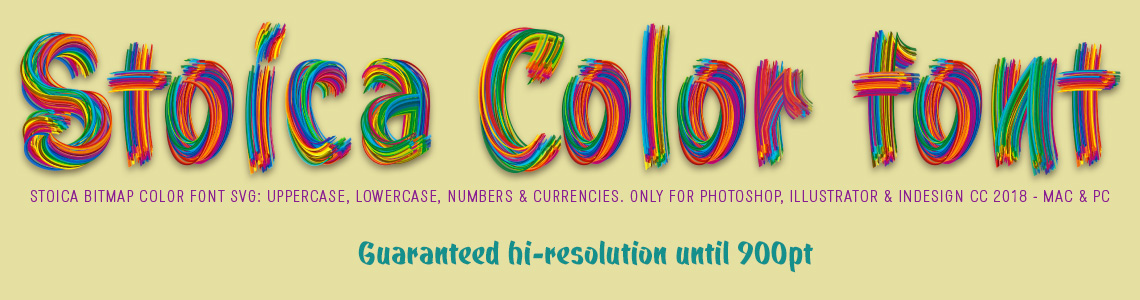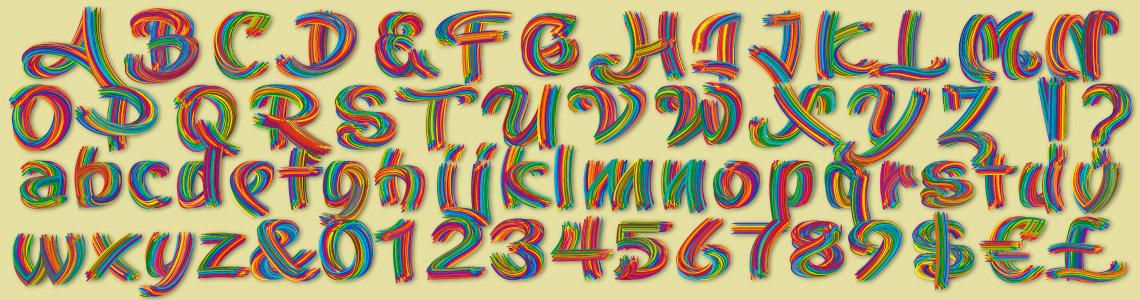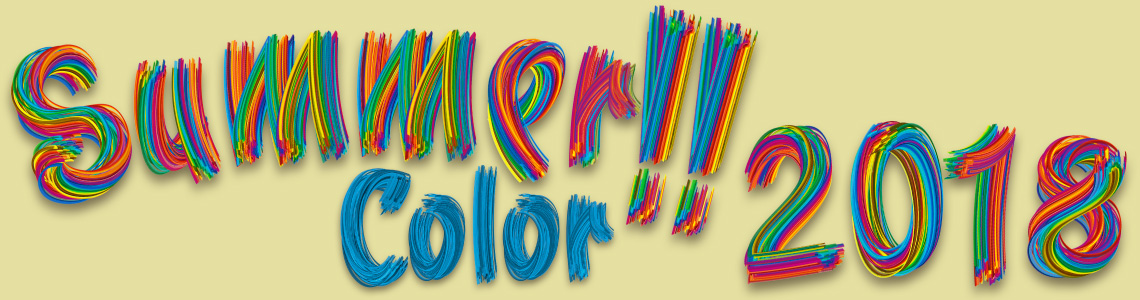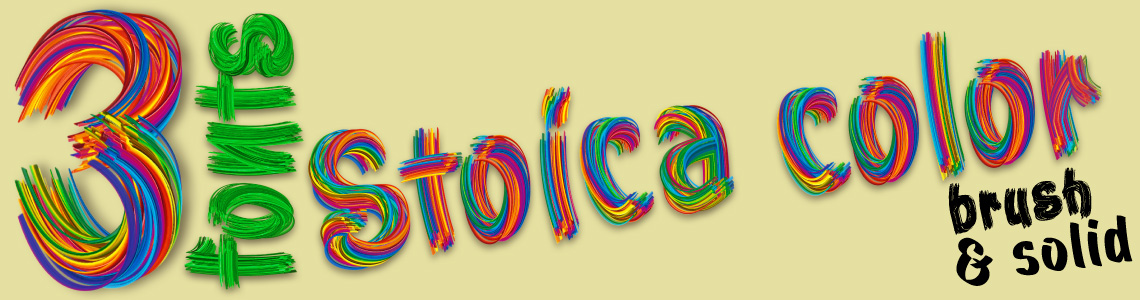
Stoica Brush
Estilo: Color font, Handwritten, Calligraphic, Script, Brush
Proporción: Condensada, Solid, Brush
Stoica es una tipografía manuscrita y condensada de estilo caligráfico en tres versiones:
- Stoica Color: Es una fuente Bitmap diseñada con trazos pictóricos multicolores 3D en alta resolución hasta 900pt. Este nuevo formato de archivo (OpenType-SVG) es sólo compatible con Adobe Photoshop, Illustrator e Indesign de las versiones CC 2018. Se puede instalar en las últimas versiones de Windows y Mac OS. Debido al gran tamaño del archivo de fuente he incluido sólo las mayúsculas, minúsculas, números, símbolos monetarios, puntuación básica y los acentos diacríticos para componer frases en idiomas latinos. TIP: Para la mejor visualización de la fuente en Photoshop usar la opción Anti-Aliasing: Redondeado.
- Stoica Brush: Versión vectorial imitando el trazo de la fuente anterior, compatible con todas las aplicaciones en formato .ttf y .otf.
- Stoica Solid: Versión vectorial de la fuente original, sin trazos de pincel, usada para crear las dos anteriores.
Stoica es ideal para diseñar posters, grandes titulares llamativos donde se busque un contraste entre este estilo manual frente a las fuentes neutrales como las Sans o las Serif.